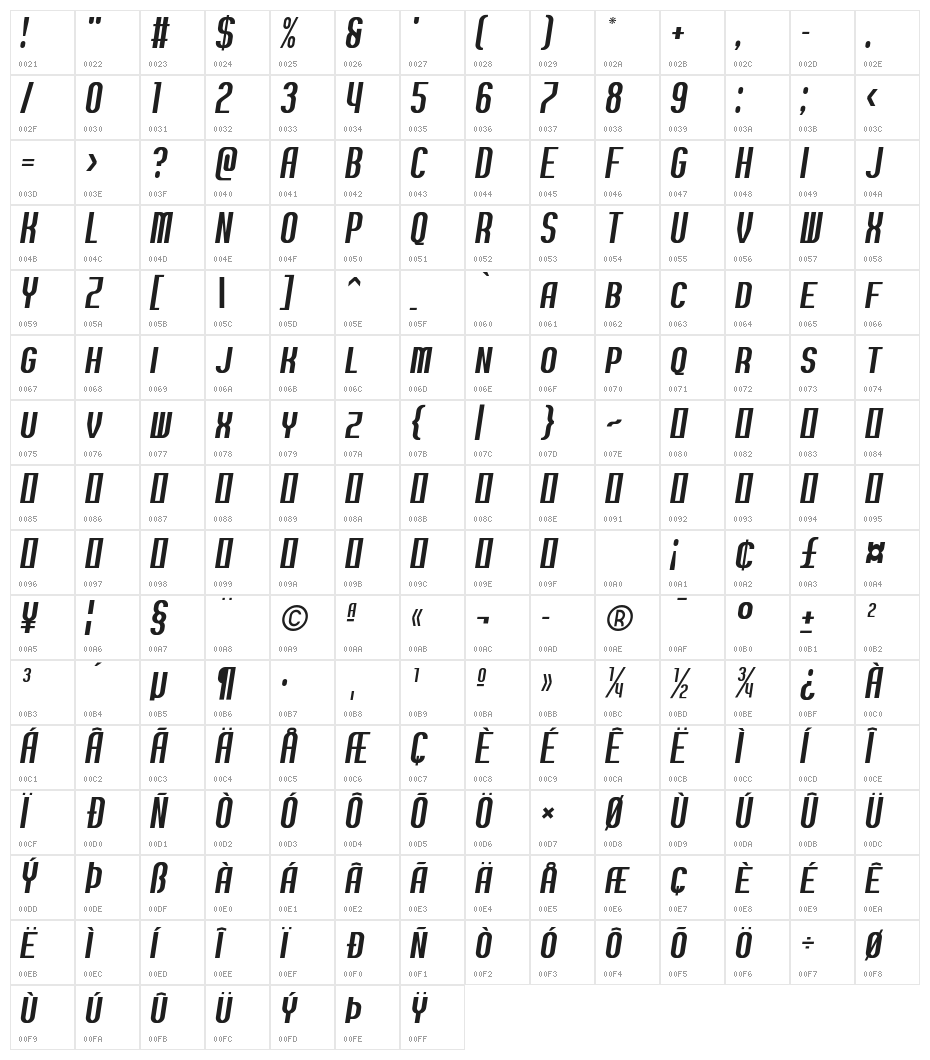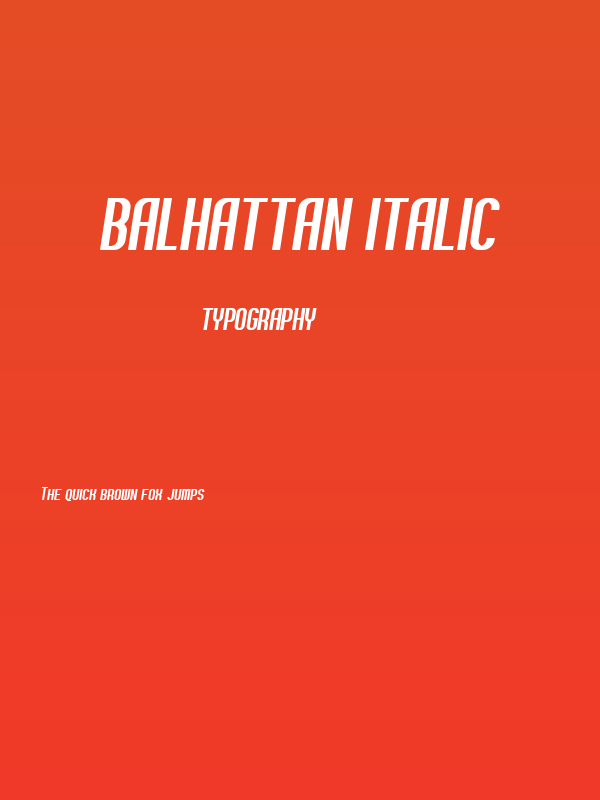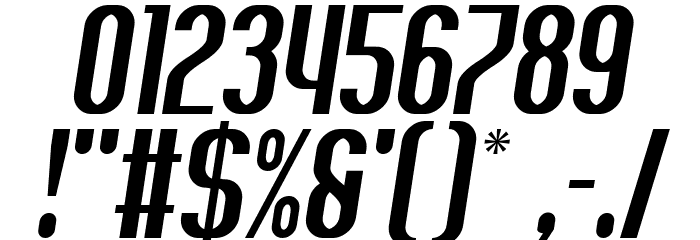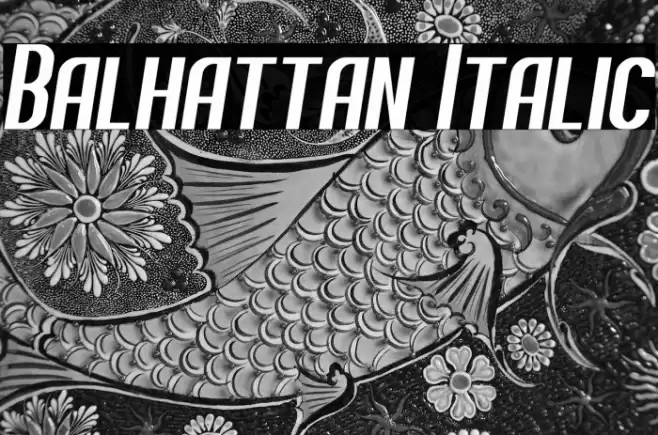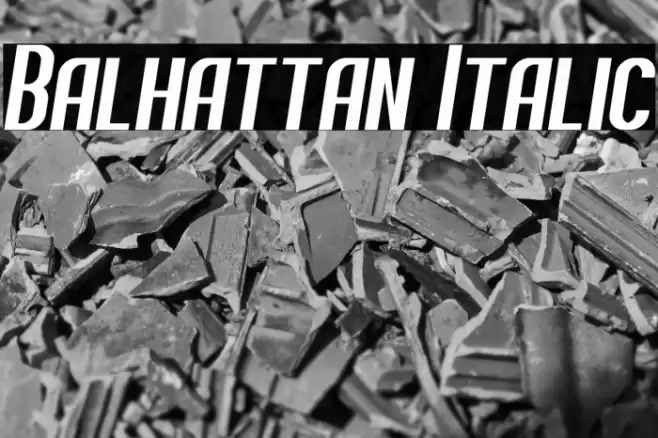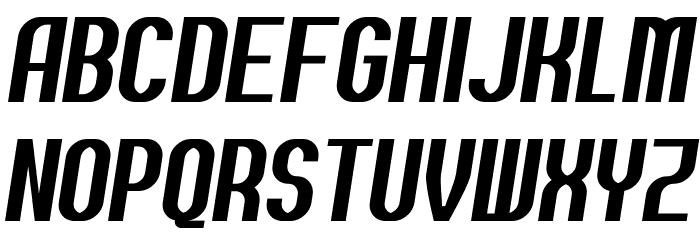
Balhattan Italic Font
| Vorgeschlagene Projekte | Ideal for branding, advertising, headlines, and poster designs where a strong, modern impression is desired. |
Balhattan Italic